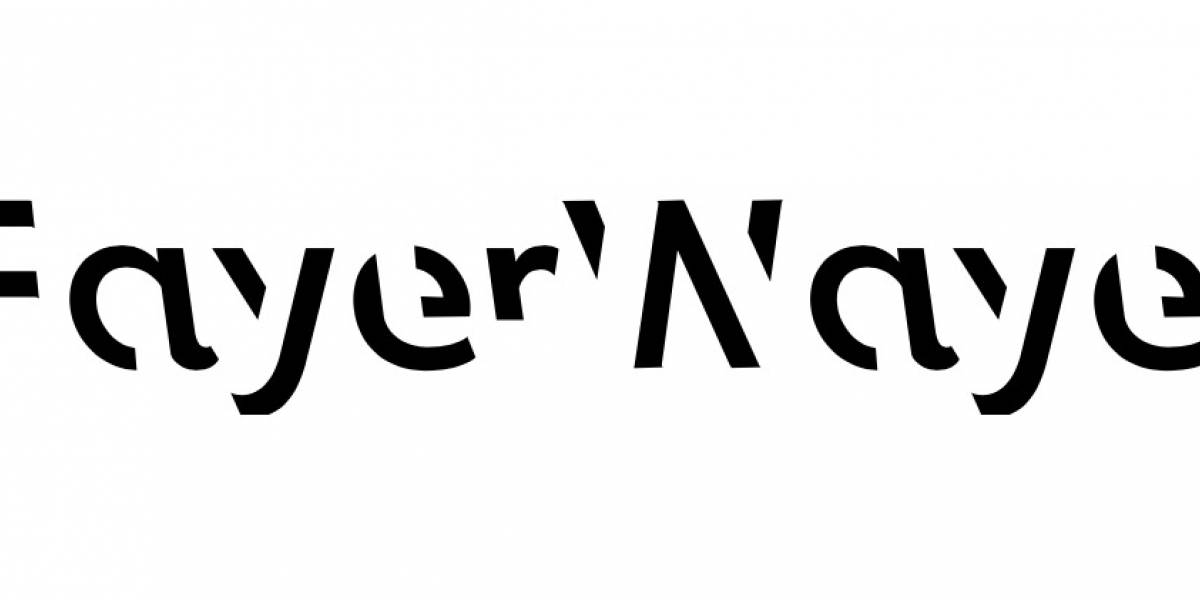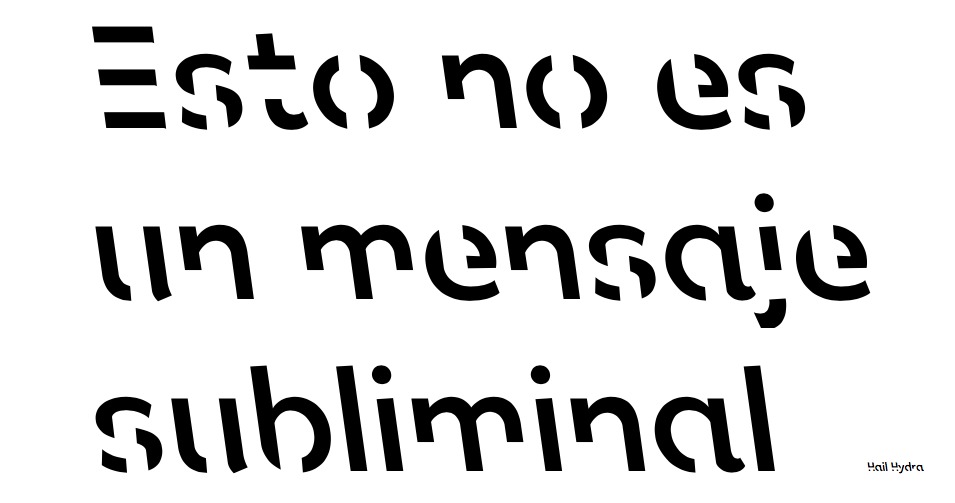
Sans Forgetica, la tipografía que te ayudará a recordar lo que leas
Sans Forgetica es una tipografía que aplica huecos e inclinación en las letras que obliga a las personas a esforzarse en su lectura y recordar más fácil.
Si por un momento te pusieras a recordar la época en la que te dedicabas al estudio (o si todavía lo haces), te vendrán a la mente los incontables y casi interminables textos que tenías que leer para pasar un examen. Si eras de los que les costaba concentrarse y olvidaba muy fácil lo que leía, la actividad podía convertirse en horas de eterno sufrimiento. Pensando en eso, se creó una tipografía especial que te ayudara a recordar: Sans Forgetica.
Todo comenzó en el Instituto Real de Tecnología de Melbourne, Australia (RMIT). Investigadores entre los que incluyen psicólogos y diseñadores tenían en mente lo fácil que era a veces olvidar la información. Por ello, desarrollaron la "la primera tipografía que fue específicamente diseñada para mejorar la retención mental".
¿Cómo funciona?
A primera vista cualquiera se daría cuenta de que es una forma poco ortodoxa de recordar una lectura. La inclinación de sus letras y los huecos en ellas no distan de cualquier tipografía "tradicional" como Arial. Sin embargo, según sus creadores, este es el punto que ayuda a mejorar el estudio.
Combinando teorías de la psicología y el diseño, se argumenta que la dificultad de Sans Forgetica hace que el lector se esfuerce por seguir el texto y así recuerde con facilidad su contenido. Así lo explica Janneke Blijlevens, especialista del RMIT:
"Las fuentes 'típicas' nos resultan muy familiares, por lo que les echamos un vistazo y no se crea rastro de memoria. Pero si la fuente es demasiado diferente, entonces nuestro cerebro no puede procesarla y tampoco se crea rastro de memoria".
Así que la clave de esto es que hubiera un punto intermedio: ni tan fácil ni tan difícil de leer. Después de mucha investigación, se diseñaron tres fuentes que debutaron en pruebas de memoria con 100 estudiantes. Al final, fue esta atípica tipografía la que resultó ganadora.
Sus creadores llaman el efecto que genera como "dificultad deseable". En teoría, más concentración puesta en la lectura ayudará a que el aprendizaje sea más completo.
¿Crees que esto es útil o solo es un desastre más para la vista?